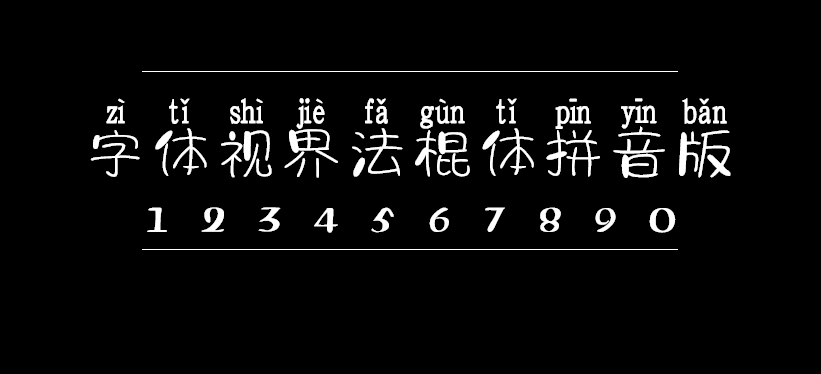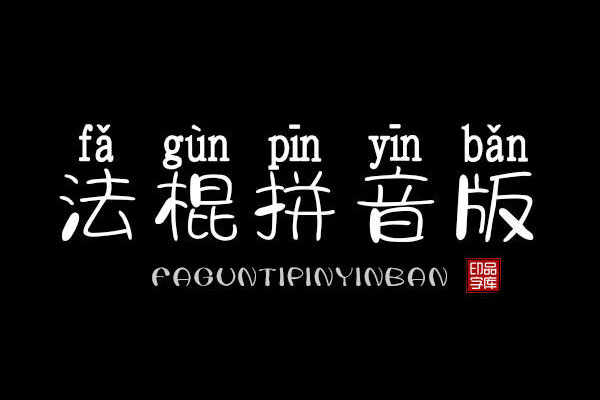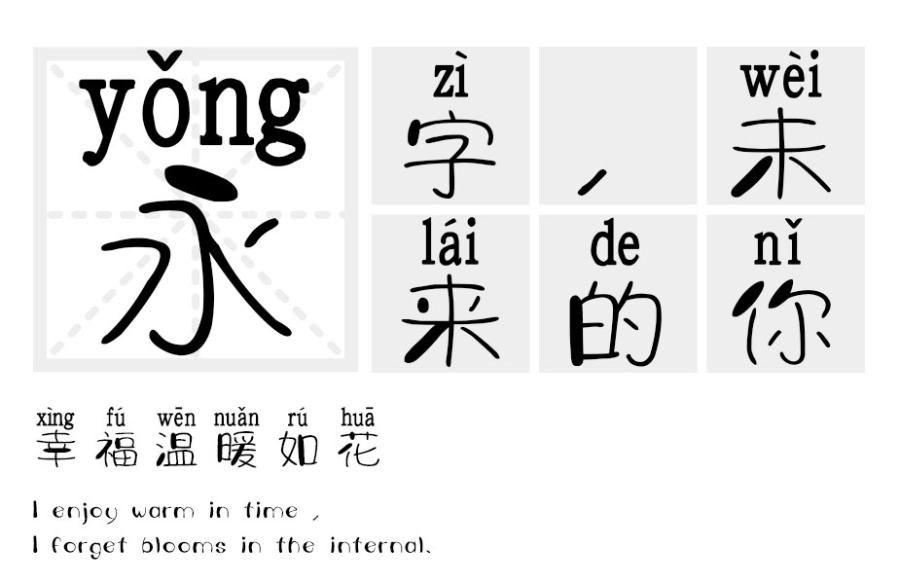
字体下载 字体视界法棍体拼音版
字体视界法棍体拼音版
字体视界法棍体拼音版是之前的免费商用字体-字体视界法棍体的修改版,加上了拼音标记,可以用来帮助学生更快地学习和阅读汉语的字体。在某些设计场景其实也挺实用的,特别是对教育类的设计会有帮助。 字体视界法棍体拼音版,同样免费开放商业授权给到所有人和商家,让所有用户可以免费使用。